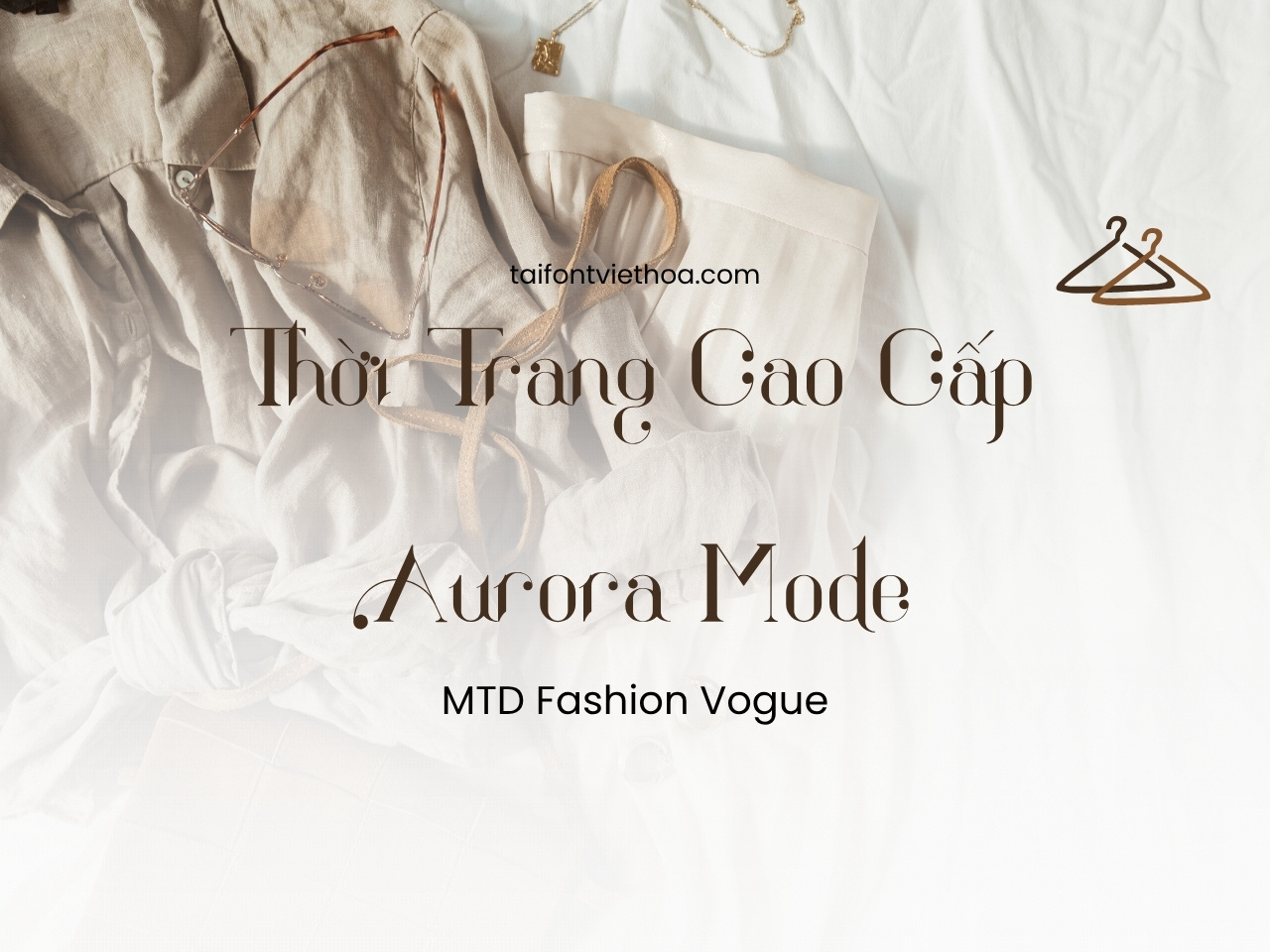
Font việt hóa MTD Fashion Vogue
Font việt hóa MTD Fashion Vogue font thời trang
Giới thiệu về font Fashion Vogue
Fashion Vogue là một font serif cao cấp mang đậm phong cách thời trang hiện đại, được thiết kế bởi Motokiwo Type (MTD). Lấy cảm hứng từ các tạp chí thời trang danh tiếng như Vogue, font này toát lên vẻ sang trọng, quyến rũ và chuyên nghiệp. Với các đường nét mạnh mẽ, đường cong tinh tế và khoảng cách chữ rộng rãi, Fashion Vogue tạo ấn tượng ngay từ ánh nhìn đầu tiên. Phiên bản Việt hóa được chính MTD thực hiện, hỗ trợ đầy đủ tiếng Việt và hơn 70 ngôn ngữ khác, đảm bảo phù hợp cho các chiến dịch thương hiệu quốc tế hoặc đa ngôn ngữ.
Đặc điểm thiết kế và ứng dụng của font Fashion Vogue
Font sử dụng cấu trúc serif truyền thống kết hợp với các chi tiết hiện đại như đường thẳng thanh mảnh, đuôi kéo dài và tương phản nét dày – nét mảnh hợp lý. Kiểu dáng của chữ mang đến cảm giác quyền lực nhưng vẫn giữ được sự mềm mại nhờ vào những nét cong nữ tính. Bộ font còn hỗ trợ ligatures giúp thể hiện tốt các tiêu đề độc đáo và ấn tượng.
Ứng dụng lý tưởng: bìa tạp chí, logo thương hiệu cao cấp, bao bì mỹ phẩm, poster thời trang, tiêu đề website hoặc tài liệu marketing chuyên nghiệp. Ngành nghề phù hợp: thời trang cao cấp, mỹ phẩm, thiết kế thương hiệu, xuất bản, nghệ thuật, studio ảnh và các thương hiệu theo đuổi phong cách thời thượng, chuyên nghiệp.